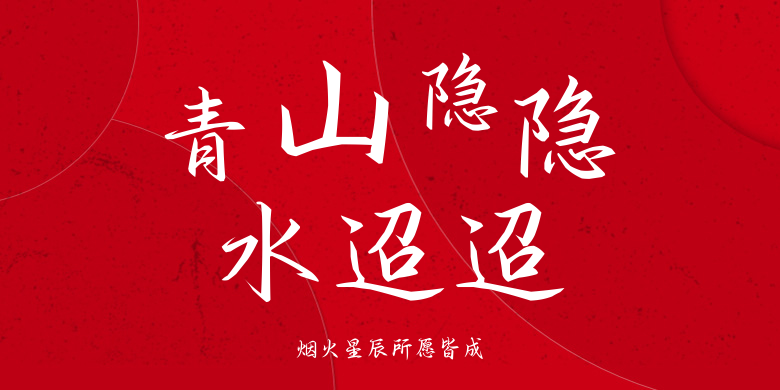
烟火星辰所愿皆成
烟火星辰所愿皆成,这款字体结构工整、笔画清晰,兼顾美观与易读性,适用于标题、正文、海报、包装、LOGO 等多种场景。字形优雅稳定,风格百搭耐看,适配日常排版与创意设计,让文字呈现更舒适、更具质感。烟火星辰所愿皆成一笔一画,皆是细节,以均衡的比例、流畅的线条打造舒适视觉体验,字形端正大气,风格简约现代。无论是商业设计、品牌宣传还是日常排版,都能轻松驾驭,让文字更有格调与力量。烟火星辰所愿皆成字体下载。